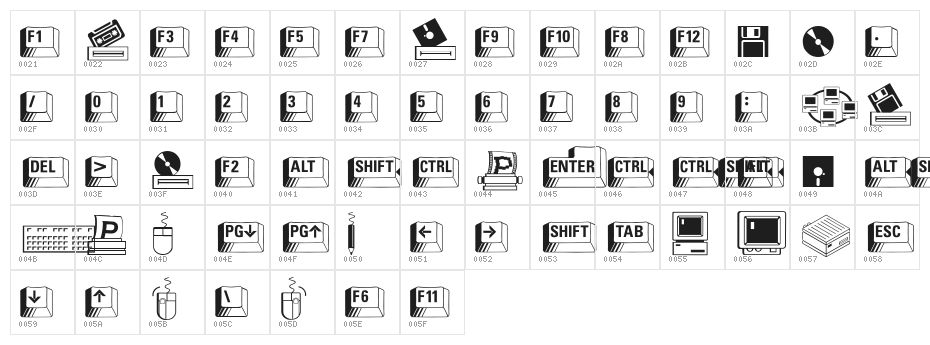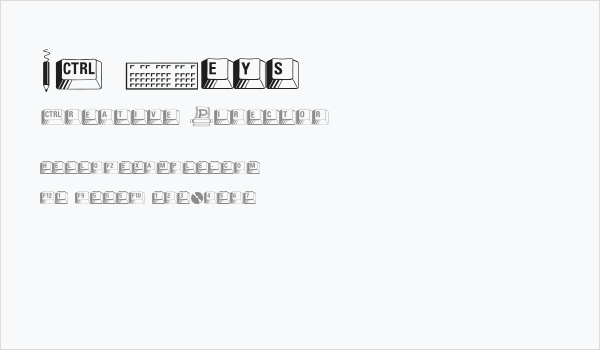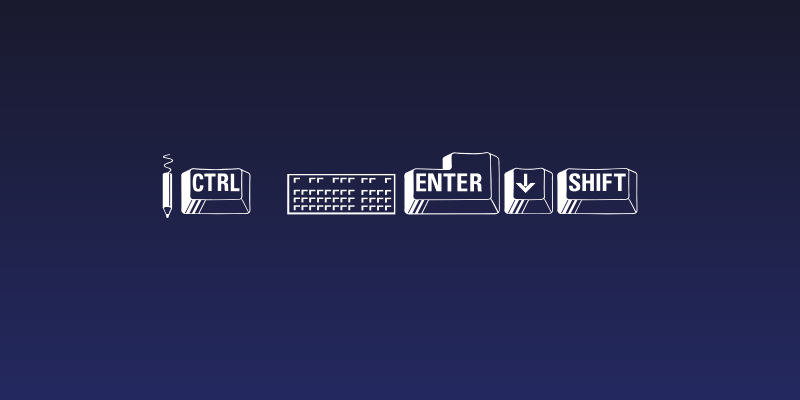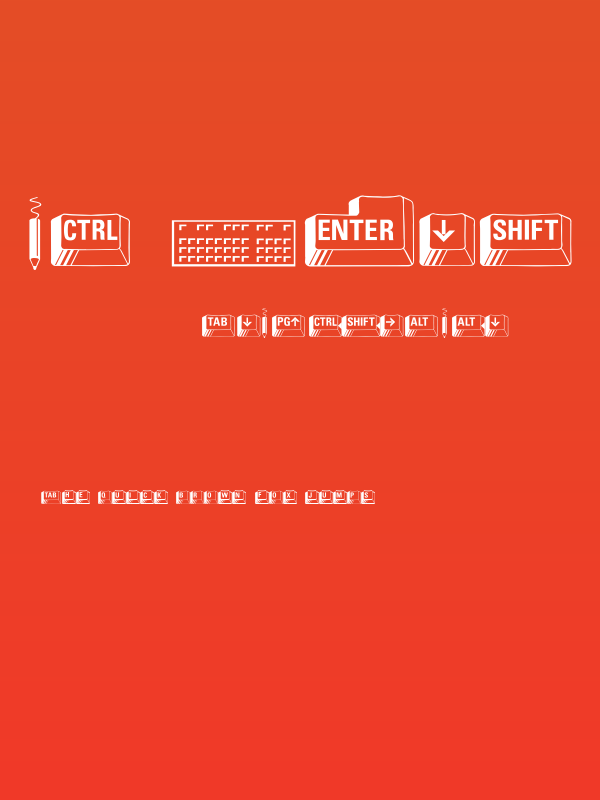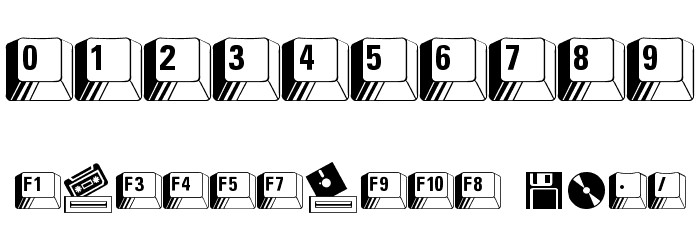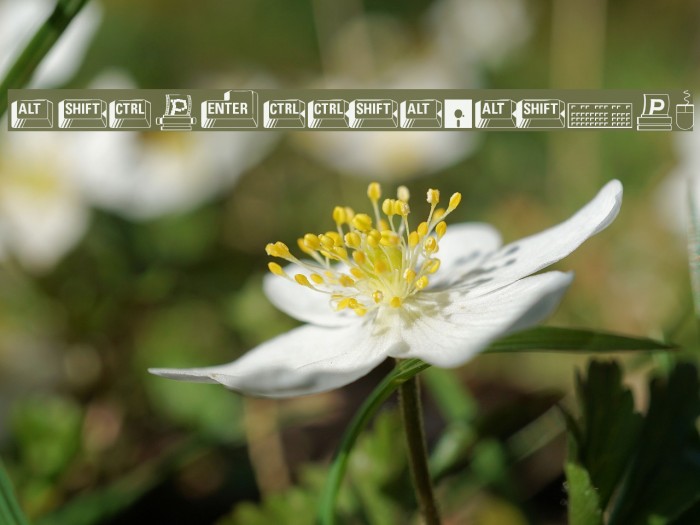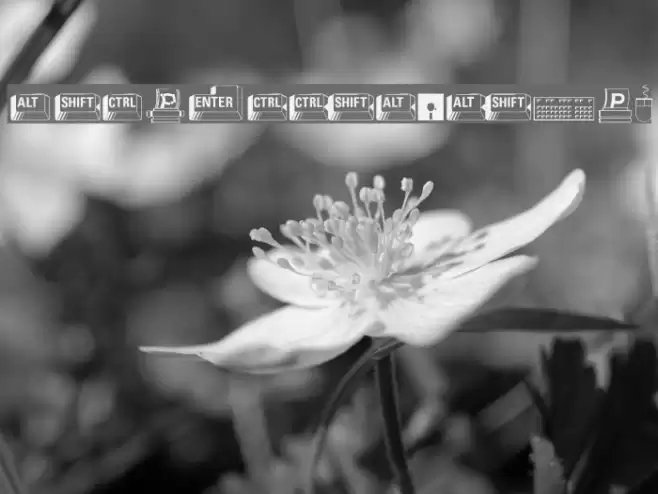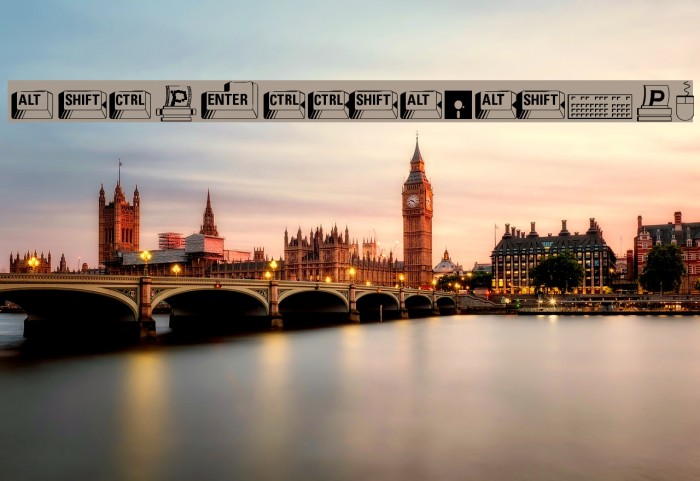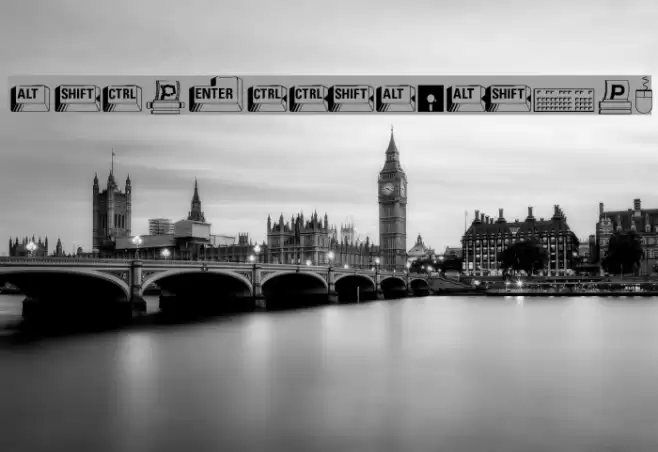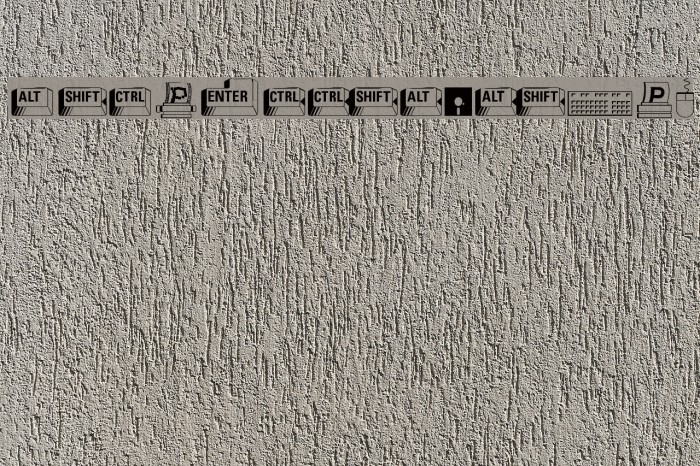
PC Keys Font
| Caso de uso | Logos, Posters, Themed Events |
| Proyectos propuestos | Ideal for tech-themed designs, retro computer graphics, educational materials about computing, or any project needing a unique, keyboard-inspired look. |